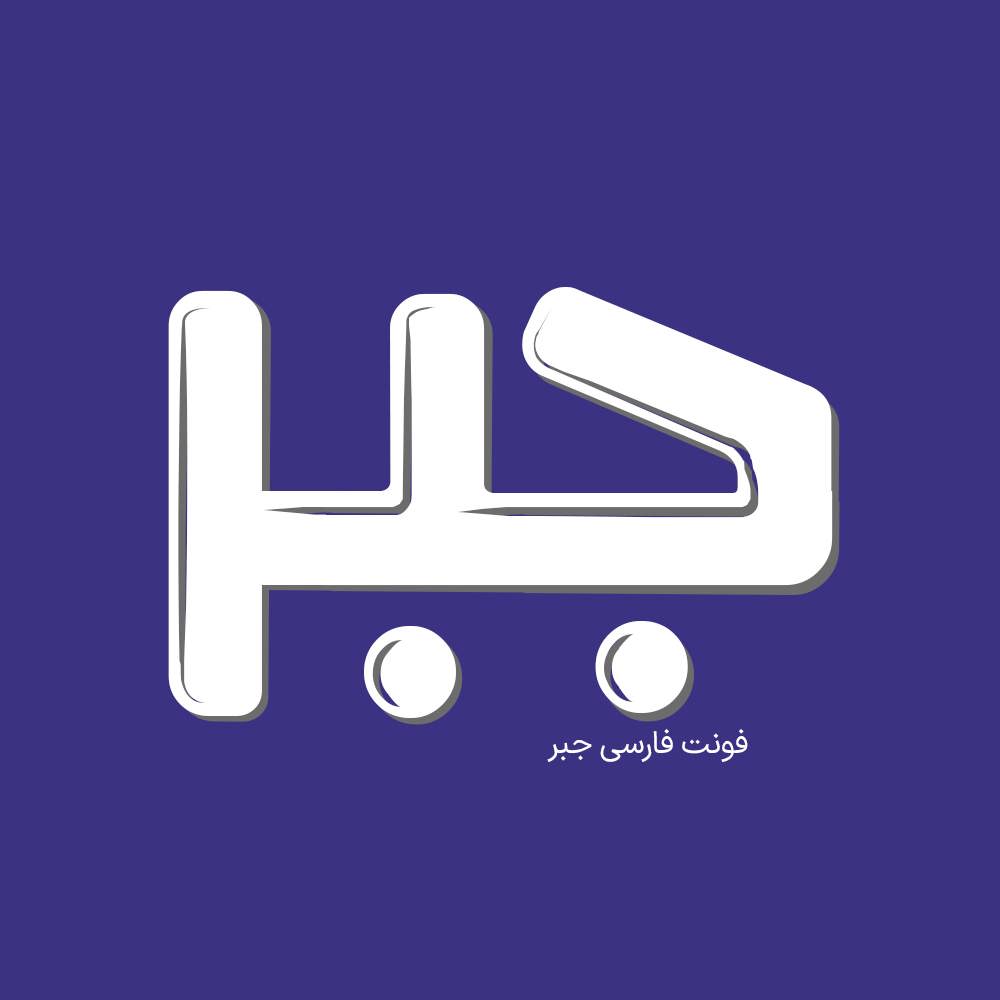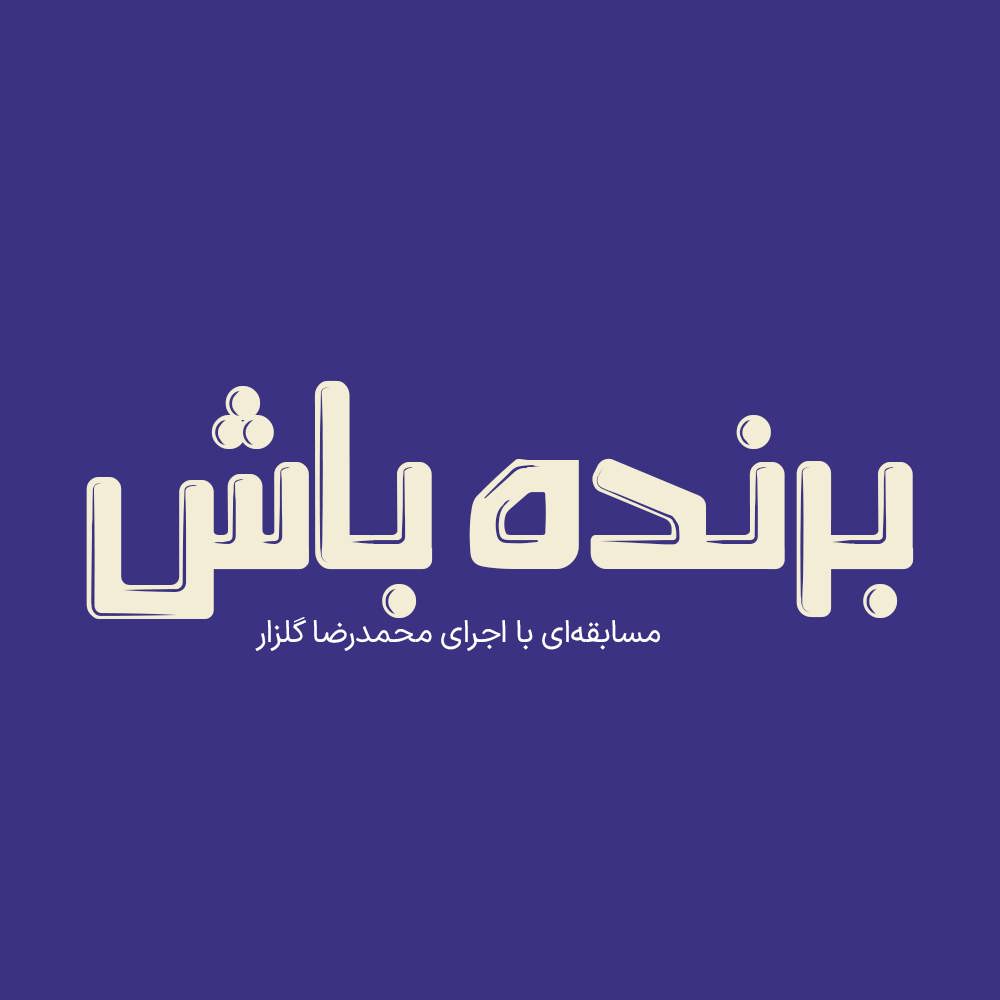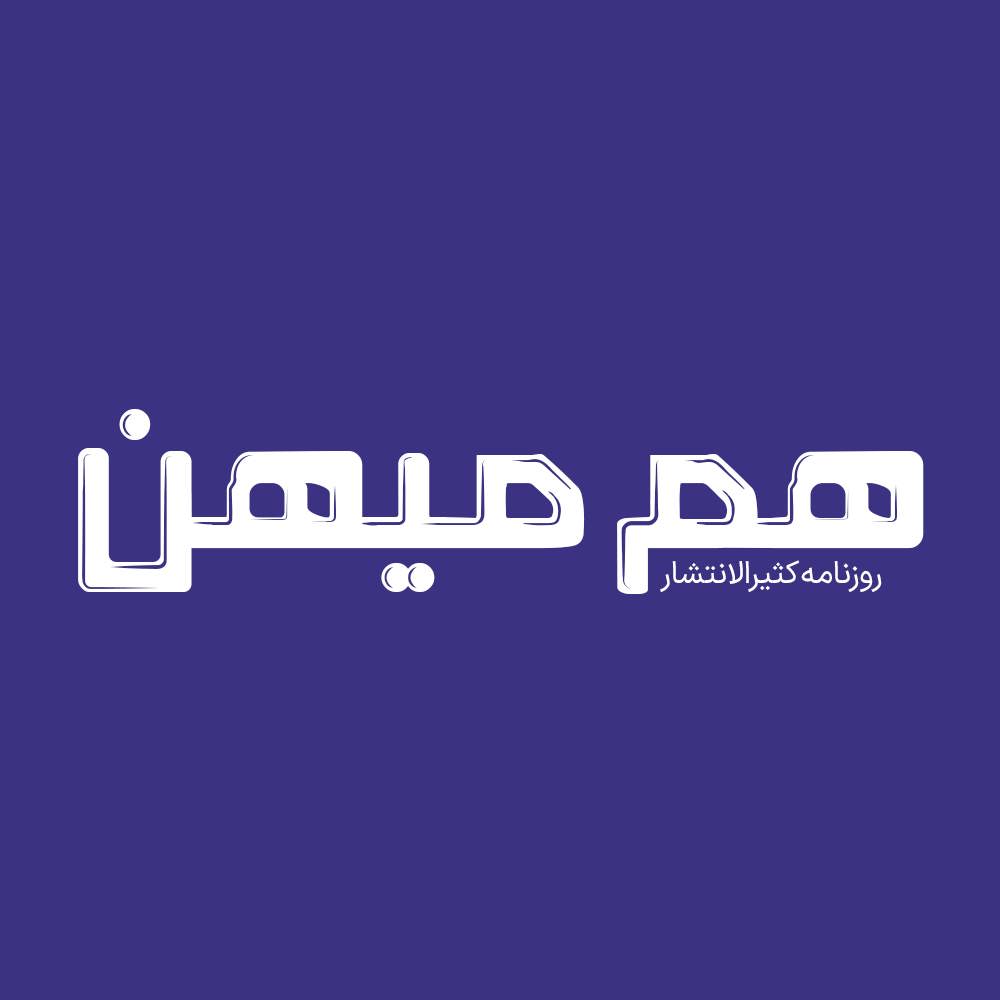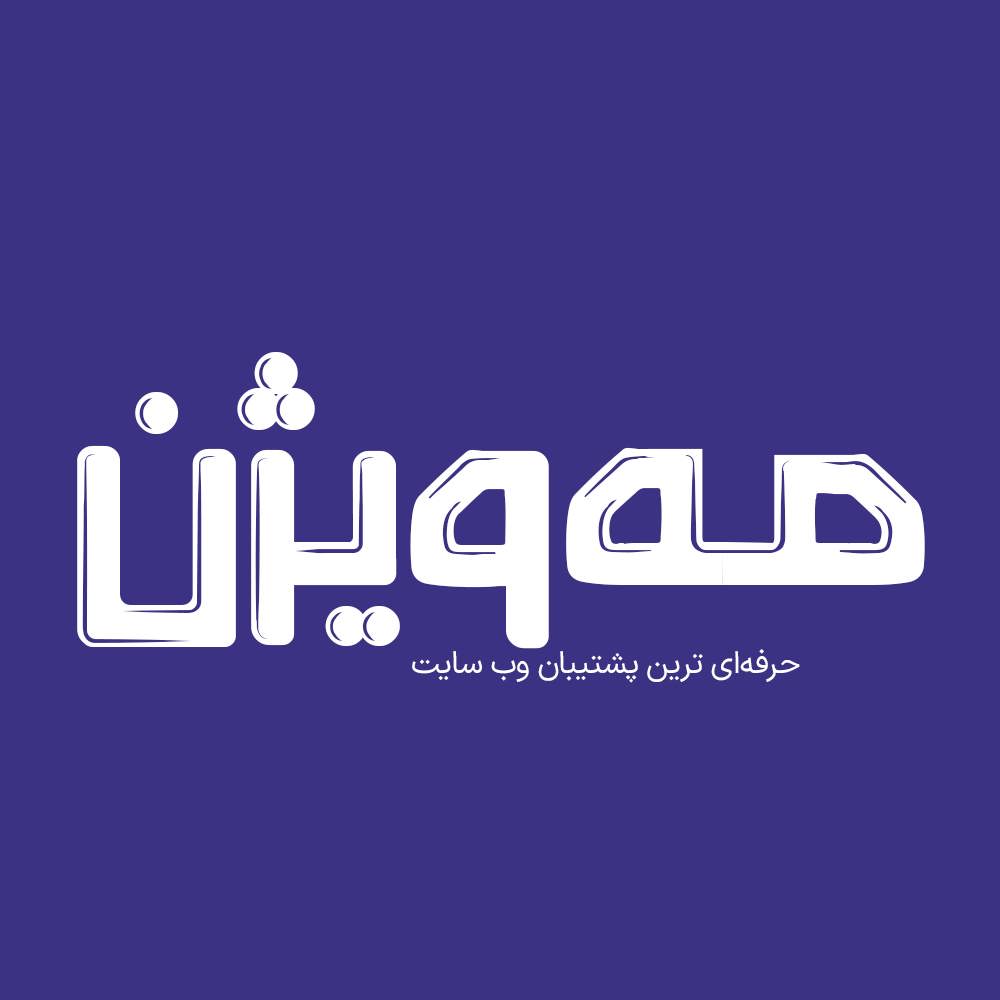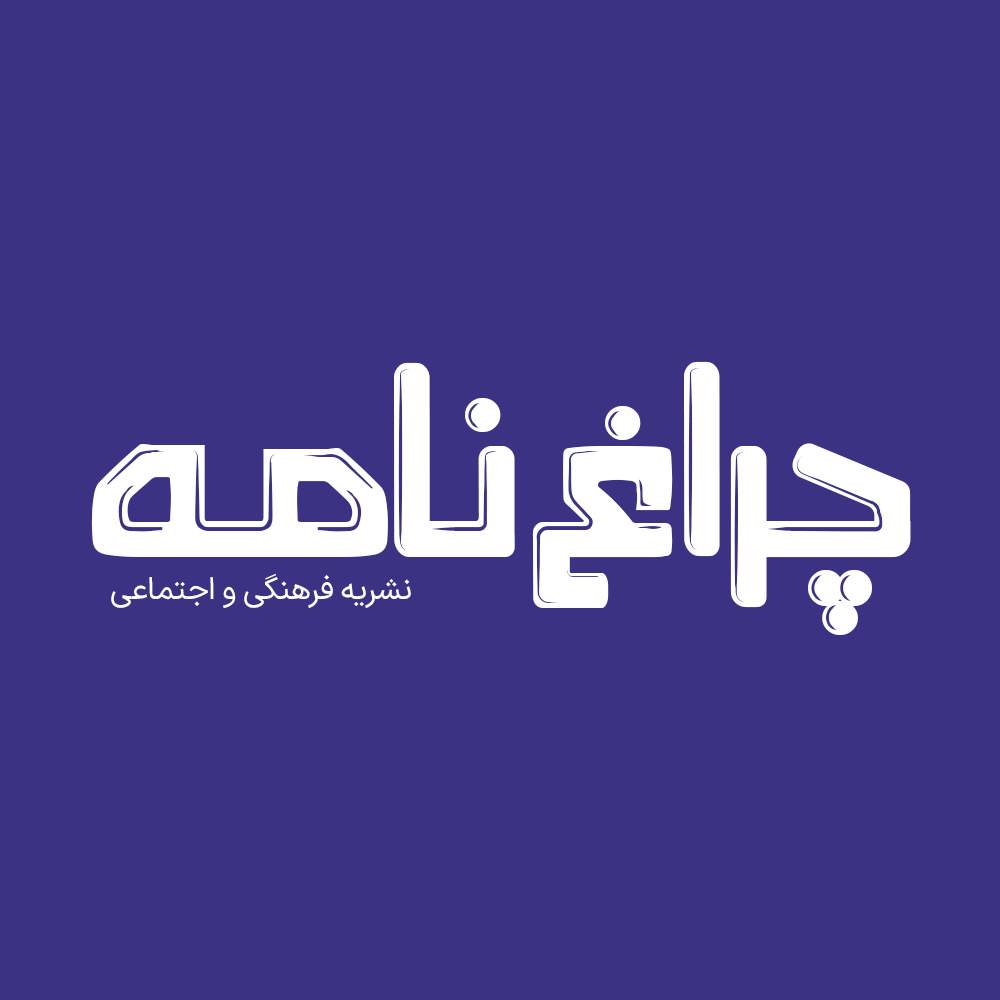
فونت فارسی جبر Jabr Font
فونت فارسی جبر یک فونت تک وزن با کاربرد طراحی لوگوتایپ و طراحی های مختلف همچون کتاب و تولید محتوای متن های کوتاه و عناوین می…
فونت فارسی جبر یک فونت تک وزن با کاربرد طراحی لوگوتایپ و طراحی های مختلف همچون کتاب و تولید محتوای متن های کوتاه و عناوین می باشد. این فونت با ساختار حروف خود مناسب استفاده در لوگوهای نوشتاری می باشد. همچنین از این فونت در طراحی تابلوهای چلنیوم هم به دلیل ساختار منحصر به فردش می توانید استفاده کنید. از آنجایی که فونتهای عربی فاقد حروف “گچ پژ” هستند و مشکلاتی در تایپ حروف “ک” و “ی” دارند در فونت جبر حروف “گچ پژ” و همچنین اعداد فارسی و انگلیسی اضافه شده است و حروف “س، ش، ص، ض، ع، غ، ق، ل، ن، ی، ئ و…” بازطراحی و بهینه شده اند تا بتوانید تمامی متن فارسی را به وسیله این فونت تایپ کنید. در ادامه برای شما نمونه تایپ های این محصول حرفه ای رو آماده کردیم که میتونید مشاهده کنید.
پیشنمایش و نمونه تایپ های فونت جبر